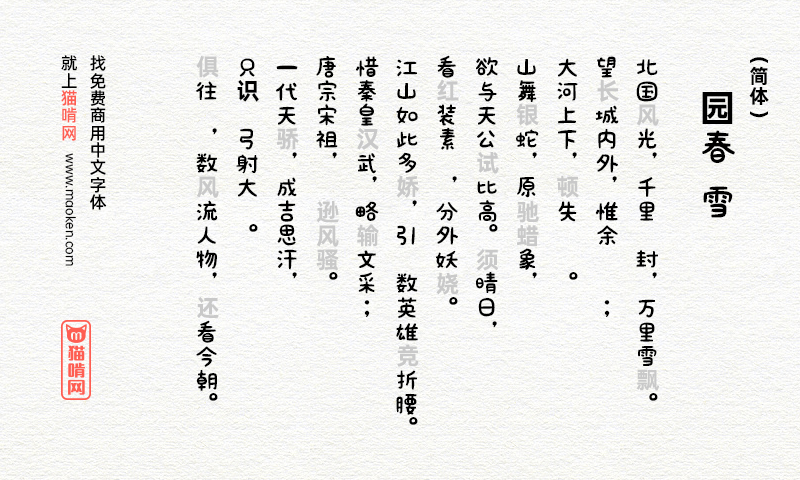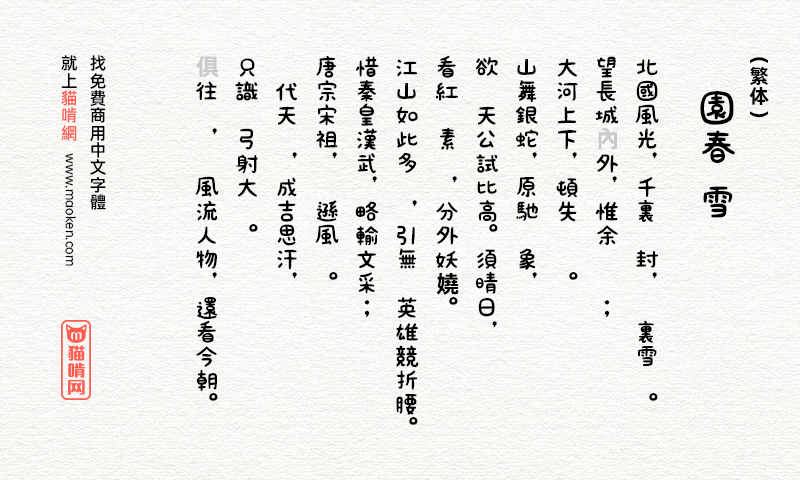
字体名称: KF手写体 | PS中字体名称:KFひま字 Regular |
字体版本:Version 1.201906 | 收录汉字: 简体★ / 繁体★★ |
这次与大家再分享「 KF手写体 」这款字体,虽然这款字体是日文字型,不过也有很多的汉字,日文字型越来越受大家的喜爱,我想应该就是有支持部分汉字的原因, 「 KF手写体 」这款是属于手写风格,整体的感觉相当相当的可爱,重点是这款字型除了个人免费使用之外,也可以商业使用,这不是超级佛心来的字体吗?
这款字体收录汉字约3000个 (JIS第1水准2965字,第2水准部分字) 。